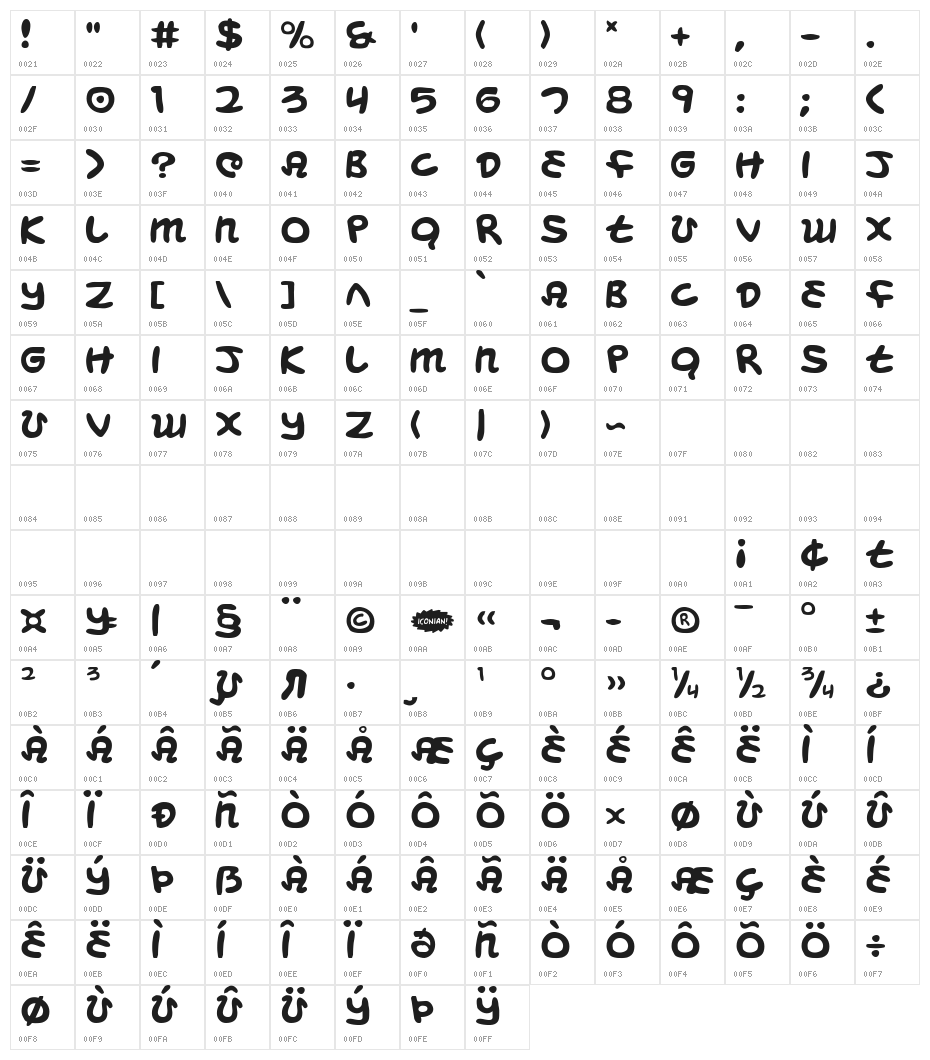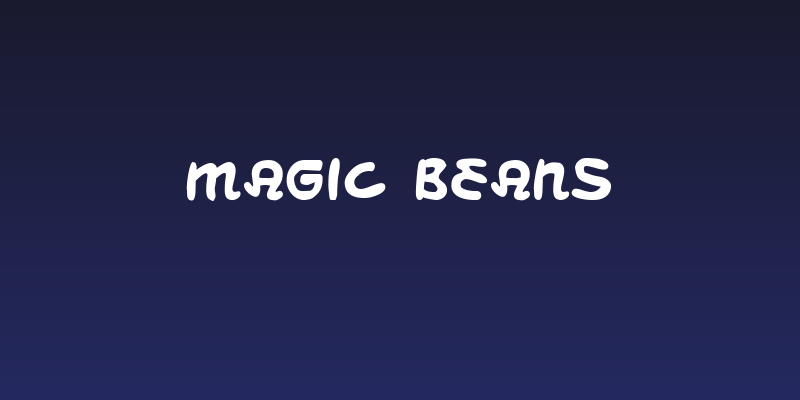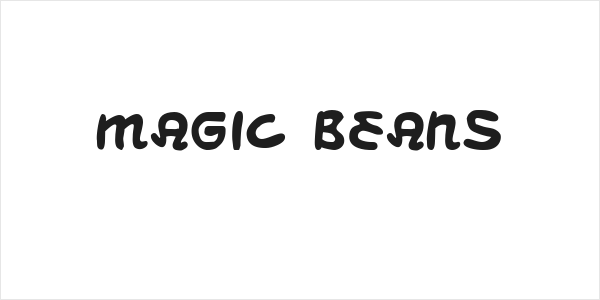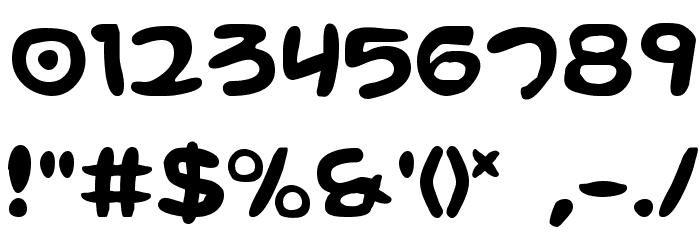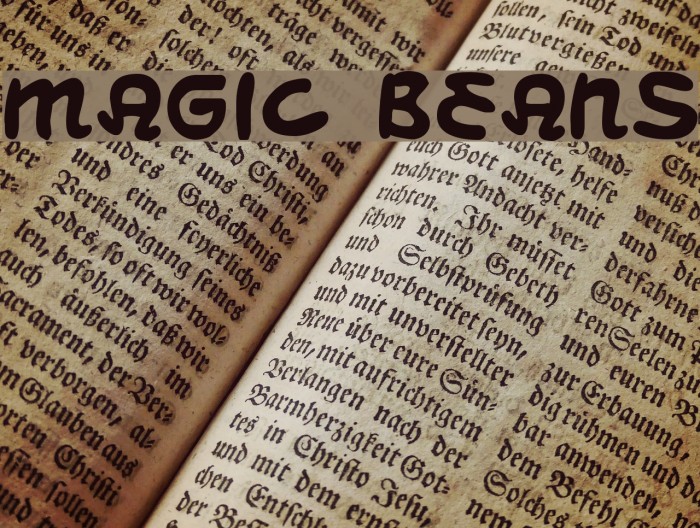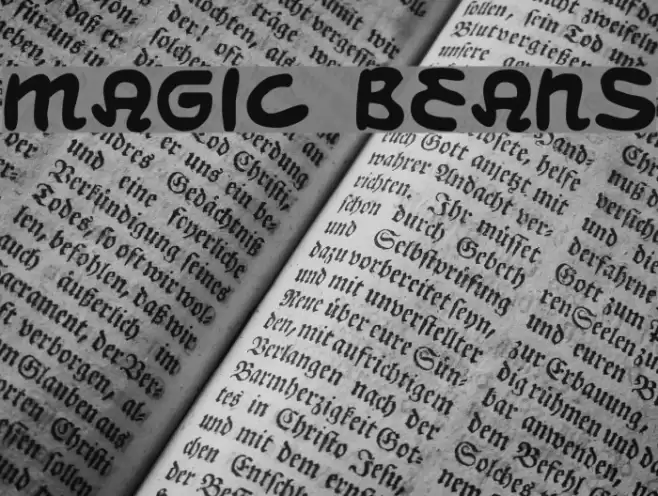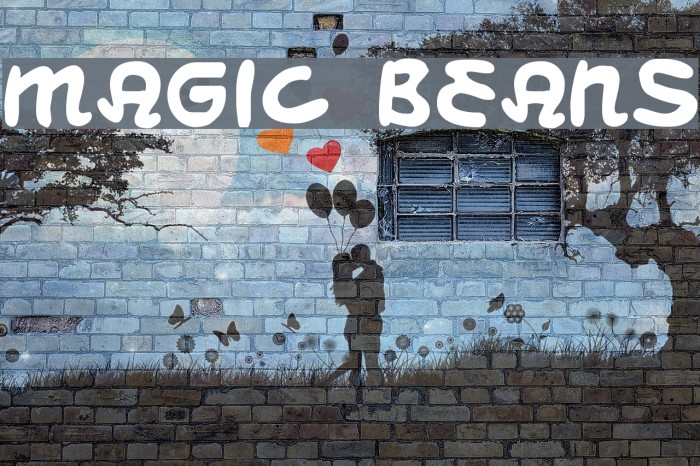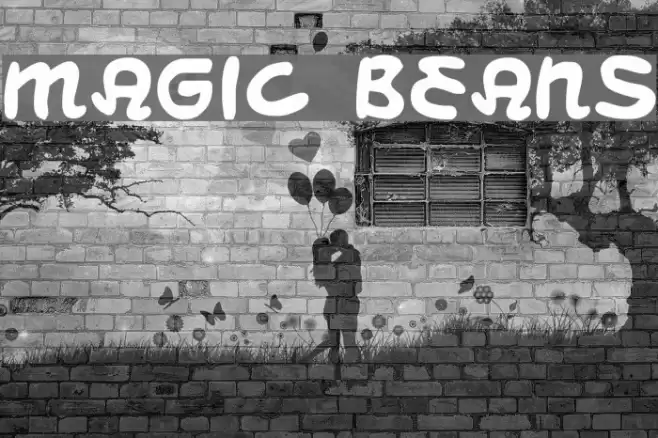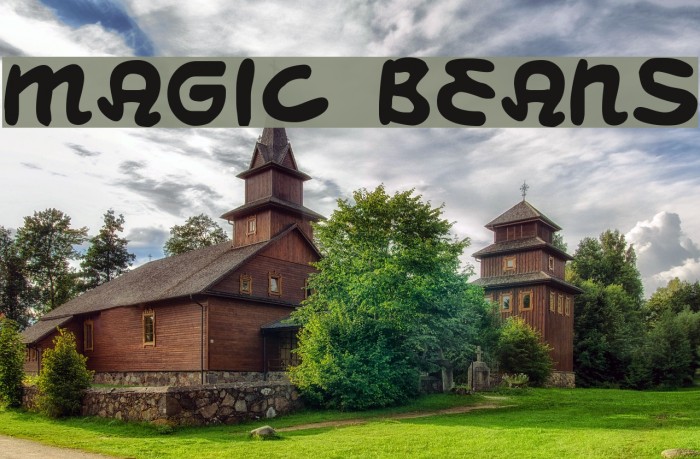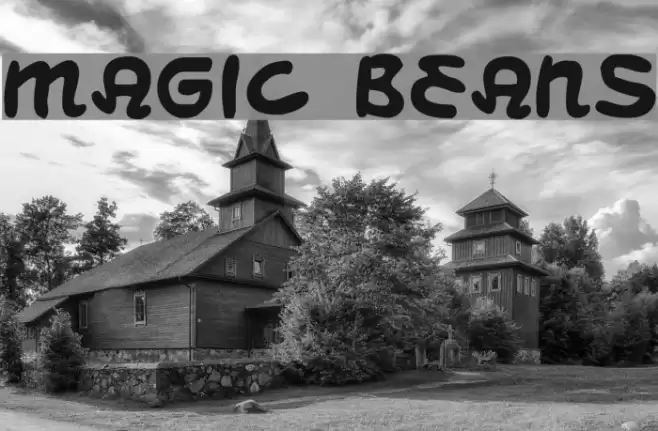
Magic Beans Font
| Gesamtstil | Casual |
| Anwendungsfall | Headlines, Logos, Informal Text |
| Vorgeschlagene Projekte | Ideal for children's books, playful branding, greeting cards, and casual invitations. |